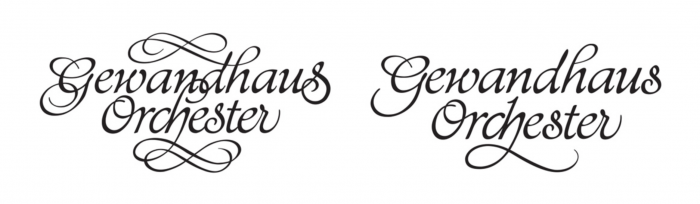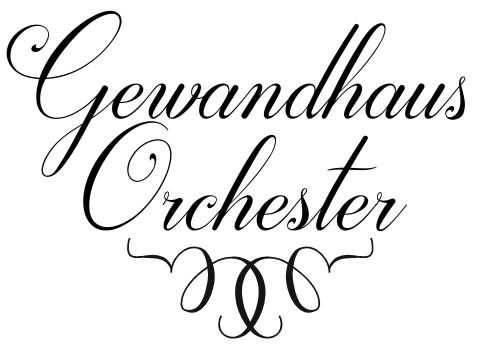
Gewandhausorchester: Logo-Redesign
Im Designtagebuch wird gerade das neue Corporate Design des Gewandhausorchesters diskutiert. Ich möchte nur mal einen einzelnen Aspekt herausnehmen und hier zur Diskussion stellen: das Logo.
Hier die Ansicht des Schriftzuges, wie er bisher aussah (links) und wie er nach der Überarbeitung aussieht (rechts):
Mich würde mal interessieren, wie Ihr die Überarbeitung seht. Für mich ist teilweise überraschend, welche Details verändert, welche beibehalten wurden. Das Ergebnis fällt in meinen Augen nicht harmonisch aus – einige Vereinfachungen wie das abrupte Abschneiden des h-Schnörkels im oberen Wort, das Abrunden einiger Buchstabenenden aber auch die formalen Lösungen, die durch Entfernen der Schmuckschleifen entstanden sind, wollen mir nicht so richtig gefallen. Ein paar Disharmonien, die auch im alten Schriftzug bereits enthalten waren, hätten in meinen Augen dringender einer Überarbeitung bedurft als die tatsächlich angefassten Formen. Ich vermute, dass es bei diesem Schritt primär um die Vereinfachung der Formen ging und das kann ja auch durchaus ein berechtigtes gestalterisches Anliegen sein. Das visuelle Gleichgewicht und die Harmonie, die die ursprüngliche Gesamtform der Wortmarke in sich hatte, finde ich im neuen Entwurf aber nicht in gleichem Maße wieder. Gerade bei den beiden s-Formen ist die Reduktion auf eine identische Buchstabenform bedauerlich. Das Trennen der Buchstaben im Wort Orchester führt dazu, dass diese unruhiger wirken, keinen rechten Halt mehr haben. Das e wirkt, als könne es jeden Moment nach rechts umpurzeln, die Lücke zum s wirkt auf mich störend. Bin ich zu kritisch?  :-?
Die einzige Optimierung für mich ist, dass das h in Orchester nicht mehr im Gewandhaus randaliert. Sonst ist es eine Übersimplifizierung. Vielleicht ist die Reduzierung im G und h des Orchesters noch gut, doch fehlt das Gegengewicht über dem Gewandhaus. Statt die Buchstabenverbünde aufzutrennen, hätte ich sie lieber so gelassen, vielleicht sogar komplett verbunden.
Also kurz: eine Verschlimmbesserung.
Die einzige Optimierung für mich ist, dass das h in Orchester nicht mehr im Gewandhaus randaliert.
Gegenüber dem Angelhaken, der jetzt das h nach oben abschließt, war das aber das kleinere Übel. Der paßt nicht so recht zu den anderen Buchstabenformen.
Interessantes Thema!
Daß im Designtagebuch diskutiert wird, kann ich nicht finden. Das übliche belanglose Zensurenverteilen.
Ich würde gern wissen, wie das ursprüngliche Zeichen von Hellmuth Tschörtner ausgesehen hat. Wenn ich es richtig gefunden habe, hat er 1967 ein Signet für ein Jubiläum entwickelt, aber ich kann mir nicht vorstellen, daß er das »h« der zweiten Zeile so in die erste eingehängt hat. Es gibt auch Versionen mit einem farbigen Streifen in der Mitte.
Die Überarbeitung ist reizlos. Der jetzige Haken am unteren »h« ist jener der kursiven Tschörtner Antiqua. Das hätte man doch einen Kalligrafen machen lassen sollen, keinen Schriftsetzer. Die charmant schiefe Mittelachse des Originals, die vielleicht auch einst eine echte Mittelachse war, hat man durch die Tilgung der Schleifen aufgegeben. Die Agentur nennt das »modernisiert und aufgeräumt«. Was vorher historisch wirkte, sieht jetzt aus wie Nachkriegsnot-Typografie aus dem Setzkasten. Einst Historie, jetzt 60er Jahre. Was ist daran modern? Ist modern, wenn man was wegläßt? So wie 1925? In unserer Zeit sollte man unter Modernität etwas eigenes verstehen, dieses »neue« Signet als Verstümmelung, als Entfernung von historischen Bezügen, ist in meinen Augen bloß unintelligent.
Zu meiner eigenen Überraschung finde ich das Redesign tatsächlich besser als das Redesignte ... was mir selten passiert.
Im alten hat man doch ein wenig die Schwünge und das Kalligrafische bzw. pseudokalligrafische übertrieben und deshalb gefällt mir die aufgeräumtere Variante besser. Die Schnörkelei oben beim alten machte ja jeden Axialsatz unmöglich, weils eben nicht axial war ...
Bezeichnend scheint mir, daß es weder auf der Website des Orchesters noch auf jener der Designagentur (oder im Design-Tagebuch-Interview) eine Erwähnung des Urhebers gibt und daß die von mir in Minuten ergoogelte Geschichte des Signets nirgends auch nur angedeutet wird. Wenn das »Live Layouting« wichtiger ist als der Gedanke eines Zeichens, das durch die Schnörkel die 1960er Jahre mit dem Jahr 1743 auf zeitgemäße und schöne Weise aus gegebenem Anlaß verbunden hat und das durch mehrfaches Absägen seiner Wurzeln und ungeschicktes Verknüpfen der Rudimente nun zum sinnlosen Stumpfknoten geworden ist, kann das Ergebnis nur bescheiden aussehen. Und dann braucht es natürlich viele bunte geometrische Architekturableitungen drumherum, damit nicht auffällt, wie fad das ist. Ein geschichtsloses Rudiment – das Orchester hat sich das mit Workshops der Agentur offenbar redlich verdient.
Die Fehler, die im ersten Logo gemacht wurden treten im Redesign wesentlich mehr hervor. Die Idee aufzuräumen ist ja nicht schlecht – dann aber richtig …
Man gucke sich mal alleine das »aus« in der ersten Zeile an. Das sind drei unterschiedliche Formensprachen/Fetten. In Martins Fundstück – dem Jubiläumslogo – sieht das anders aus.
Die Fehler, die im ersten Logo gemacht wurden treten im Redesign wesentlich mehr hervor. Die Idee aufzuräumen ist ja nicht schlecht – dann aber richtig …
Man gucke sich mal alleine das »aus« in der ersten Zeile an. Das sind drei unterschiedliche Formensprachen/Fetten. In Martins Fundstück – dem Jubiläumslogo – sieht das anders aus.
In dem Vorgänger des neuen haben auch die Schnörkel oben und unten unterschiedliche Züge und Strichstärken. Wer hat das eigentlich verbrochen, dieses schiefe Mißgeschick?
Wisst Ihr, was mich so stört? Im Original (also speziell in den ganz alten Versionen) erkennt man die Gesamtkomposition, sieht man das Handwerk – in der ganz neuen Fassung hingegen sieht es aus, als habe man die Wortmarke aus einem kalligrafischen, nicht ganz sauber digitalisierten Font zusammengesetzt, ohne das Schriftbild anschließend sorgfältig zu optimieren. Das Einzigartige und der Charme der Ursprungsidee sind für mich weitgehend verloren gegangen. Was mich auch schmerzt: Je später die Logoversion, desto unharmonischer scheint mir die Linienführung zu werden. Versteht mich nicht falsch – nicht, dass ich das aus dem Stegreif besser schreiben könnte! Aber wenn man eine solche Arbeit in die Finger bekommt, dann muss man ganz genau wissen was man tut. Oder: wer es besser könnte. Und da hätte es doch sogar direkt von Ort einen ausgewiesenen Fachmann gegeben …
Ich habe hier der Vollständigkeit und Fairness halber noch ein Zitat aus dem Interview im dt, das die Zielsetzung bei der Überarbeitung des Logos erklärt:
dt: Da das Logo (lediglich) evolutionär verändert wurde: Wie war das Briefing diesbezüglich? Könntest Du einmal die an das neue CD gerichteten Ziele formulieren.
Mich würde mal das investierte Budget interessieren, wie groß der Anteil war, der für dieses “Live Layouting” drauf ging und wieviel Spielraum überhaupt noch für die Überarbeitung des Kernelementes Logo blieb.
Das »Redesign« ist, ich muß es leider so sagen, in Wahrheit noch viel schlimmer als man auf den ersten Blick sieht. Es enthält ca. 15…20 klare handwerkliche Fehler.
Jetzt würde ich zu gerne wissen, was die Kollegen dafür eingestrichen haben.